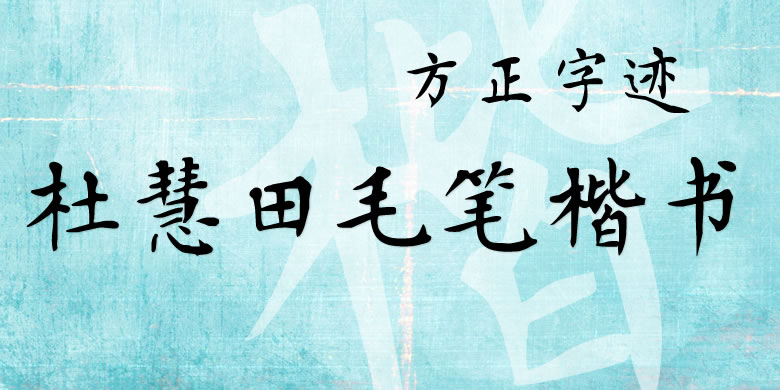
由青年书法家杜慧田创作。杜慧田,别署丑石、逸人,1970年生于山西。自幼酷嗜书学,三十多年精勤不懈,遍习历代法帖,尤对“二王”及初唐诸家研习更勤,楷宗【欧、颜】、草味【旭、素】,深信“学书以传统精华为本源,厚积薄发,融通诸家,方能入精微,致广大”。是一位正统派,功力型,软、硬笔皆善的青年书法家。方正字迹-杜慧田毛笔体,以唐欧阳询为宗,字体清雅秀丽、刚劲挺拔,大小有法、错落有致。